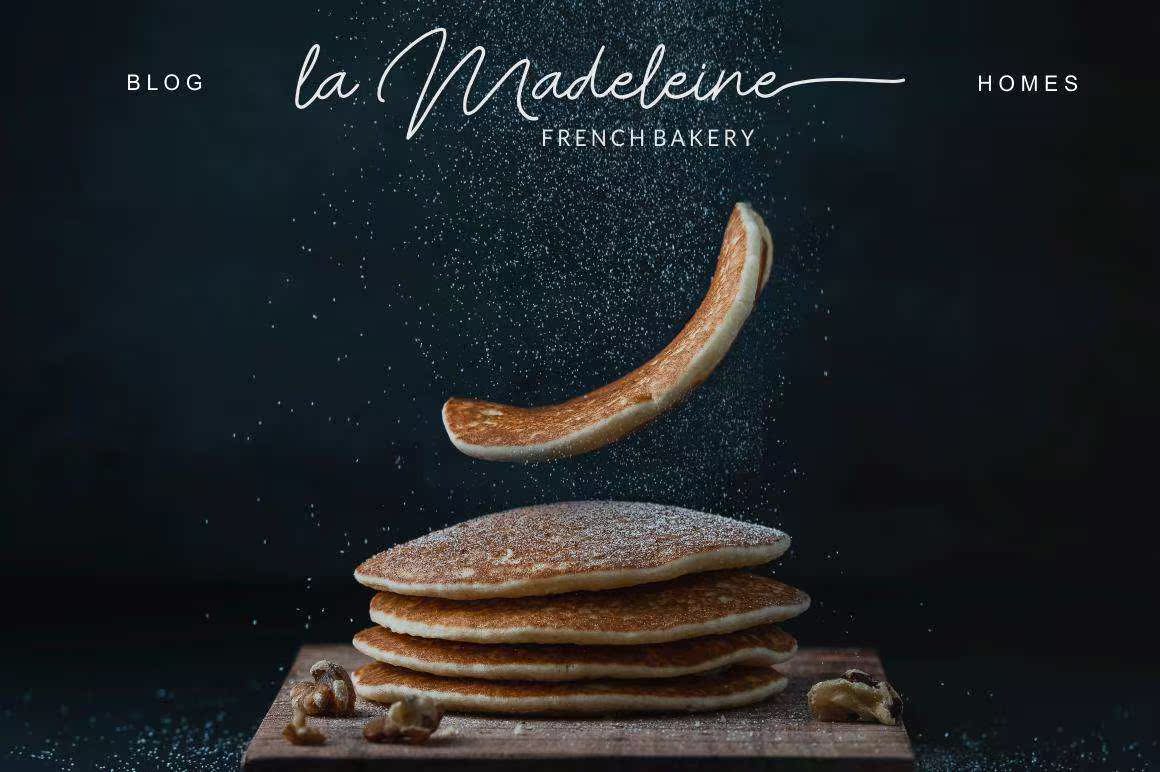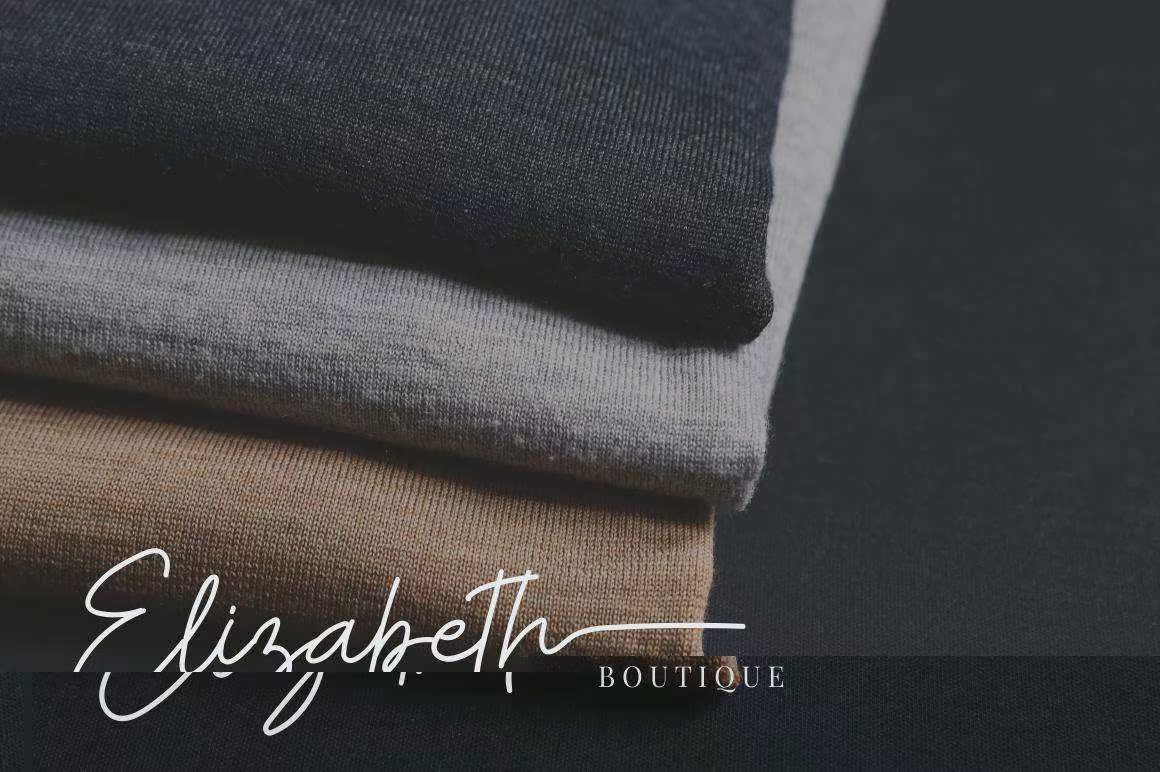
BlackColnes–以简单、优雅、时尚和华美的风格为您的下一个创作项目(包括水印摄影、签名或签名标识设计、报价、相册封面、名片和其他许多设计项目)提供随意签名和书写的手写体手写体字体。此字体非常适合您的下一个创作项目,BlackColnes可将您的工作提升到最高水平。BlackColnes–以简单、优雅、时尚和华而不实的风格为您书写的随意签名字体,此字体非常适合您的下一个创作项目,包括水印摄影、签名或签名标识设计、报价、相册封面、名片以及其他许多设计项目。从名片到Watermarks,Black Col Neiser可将您的工作提升到最高水平。